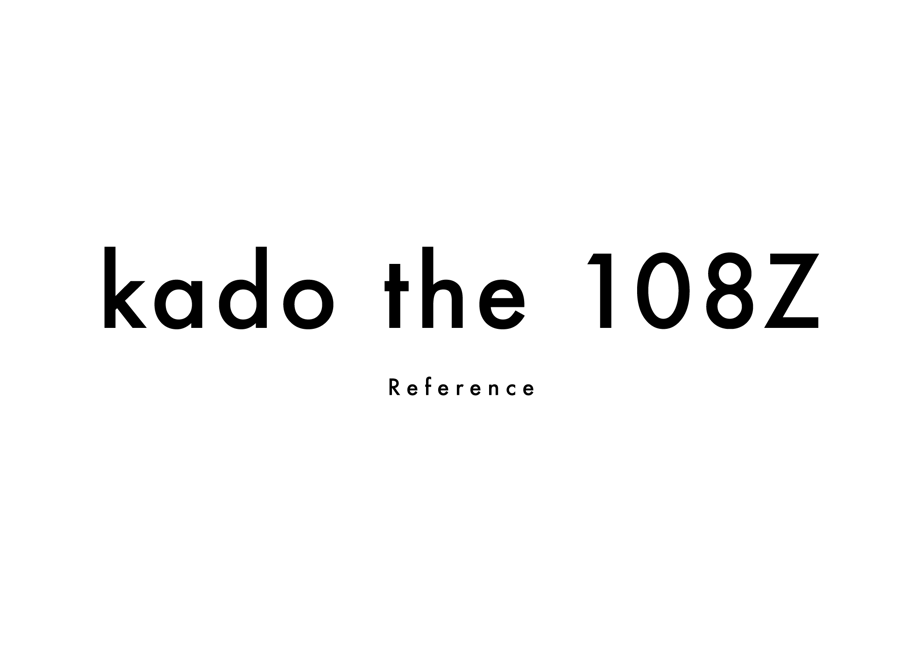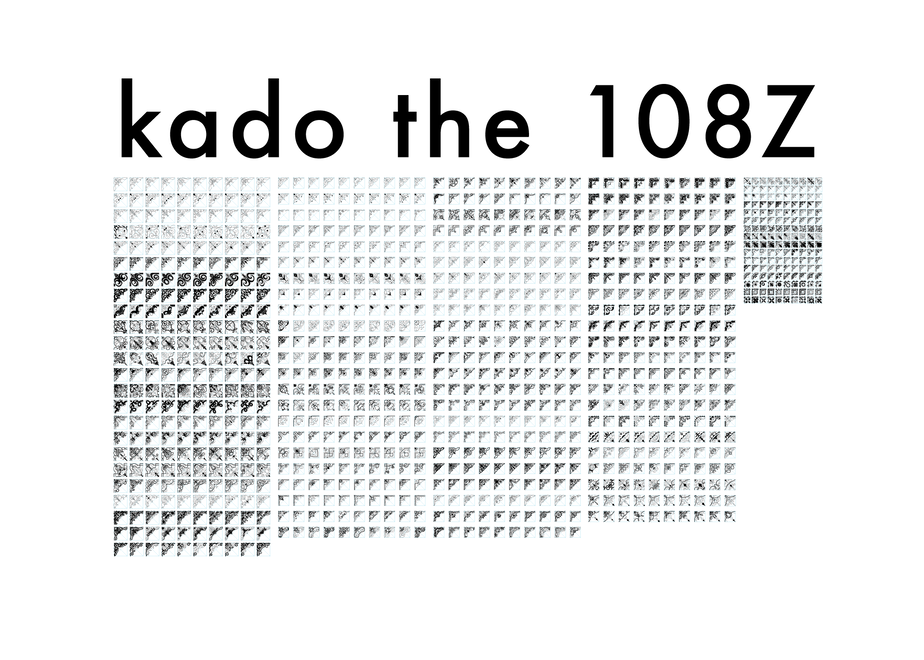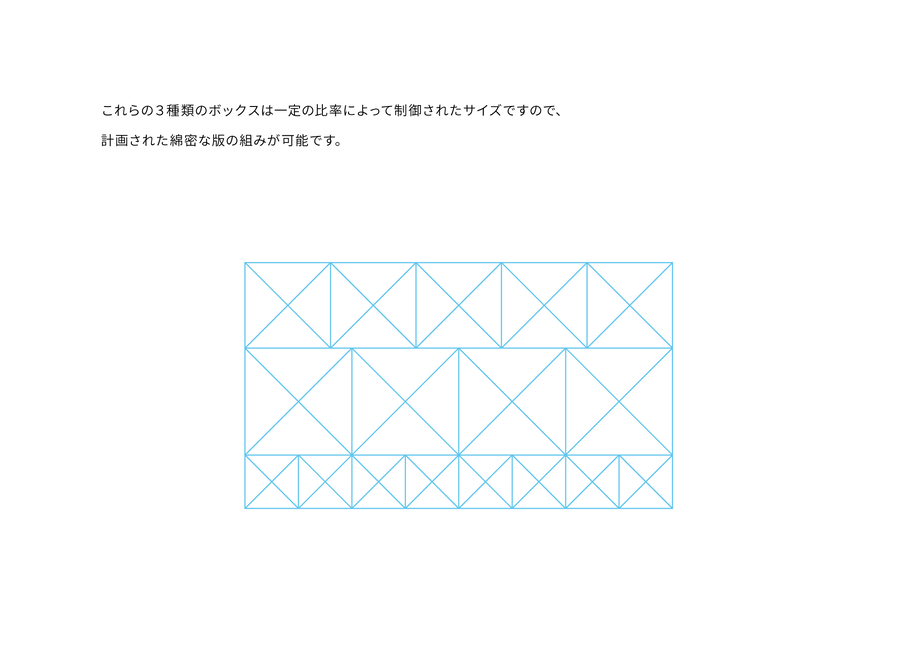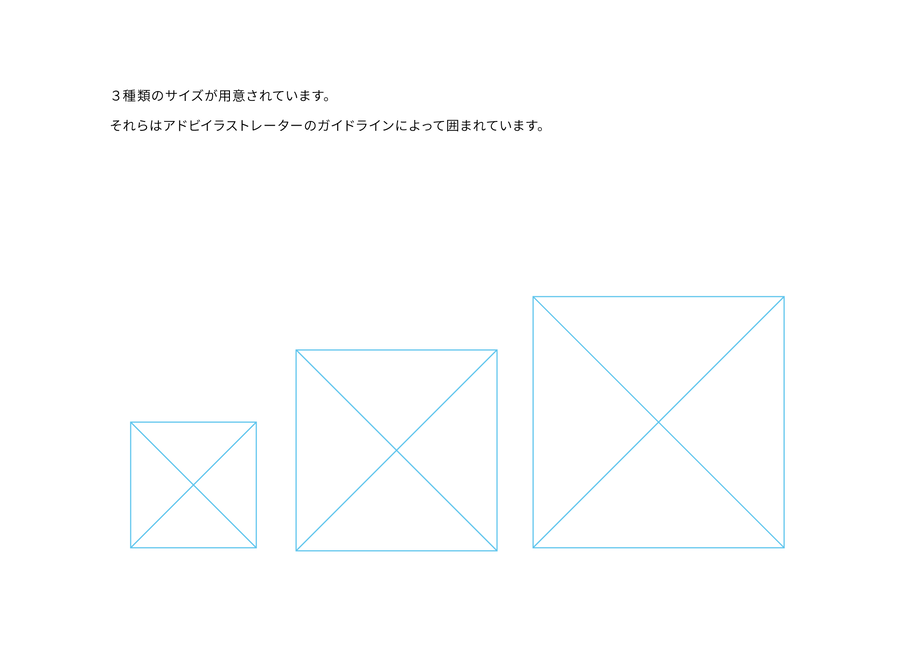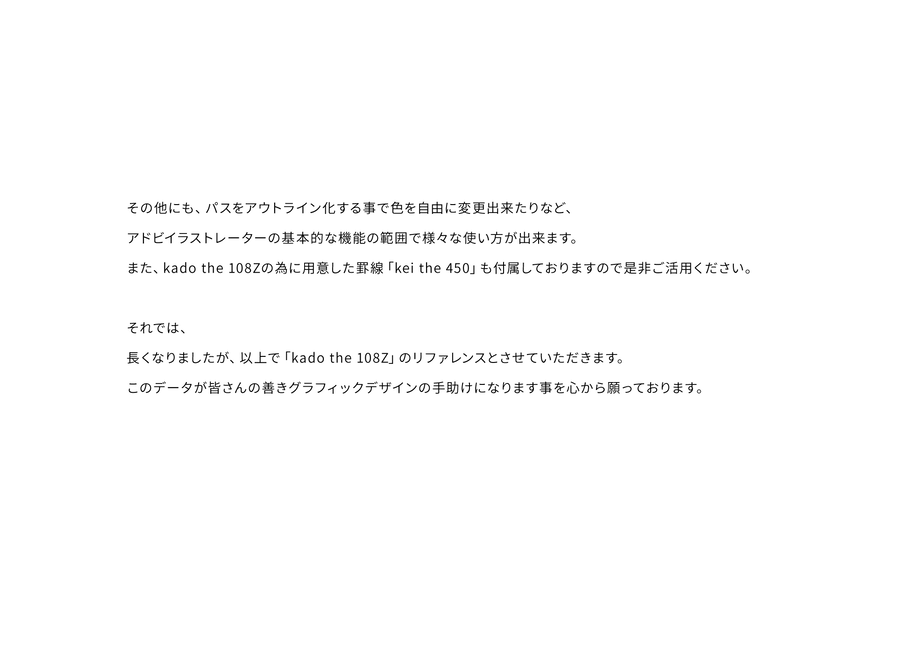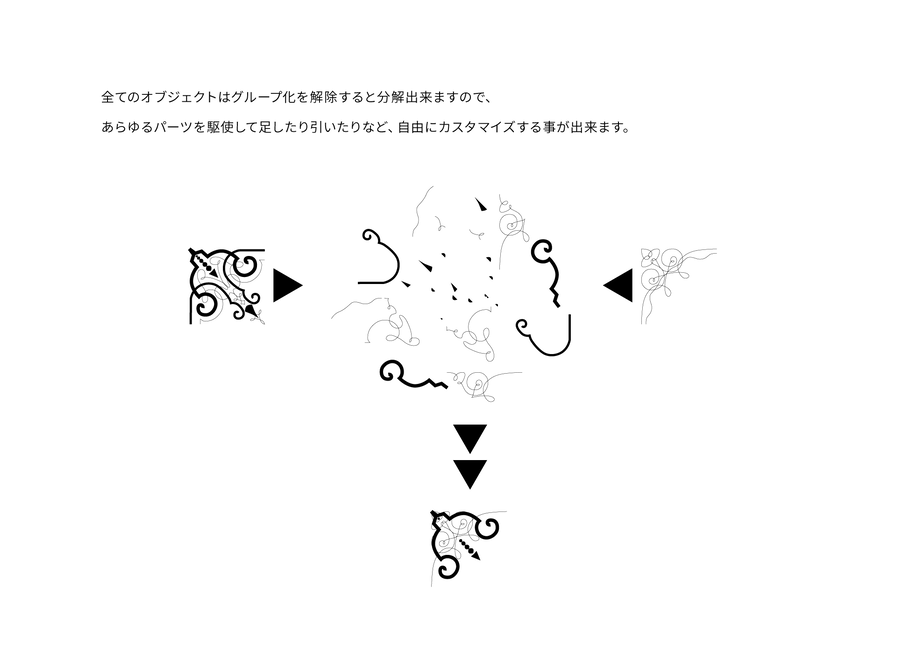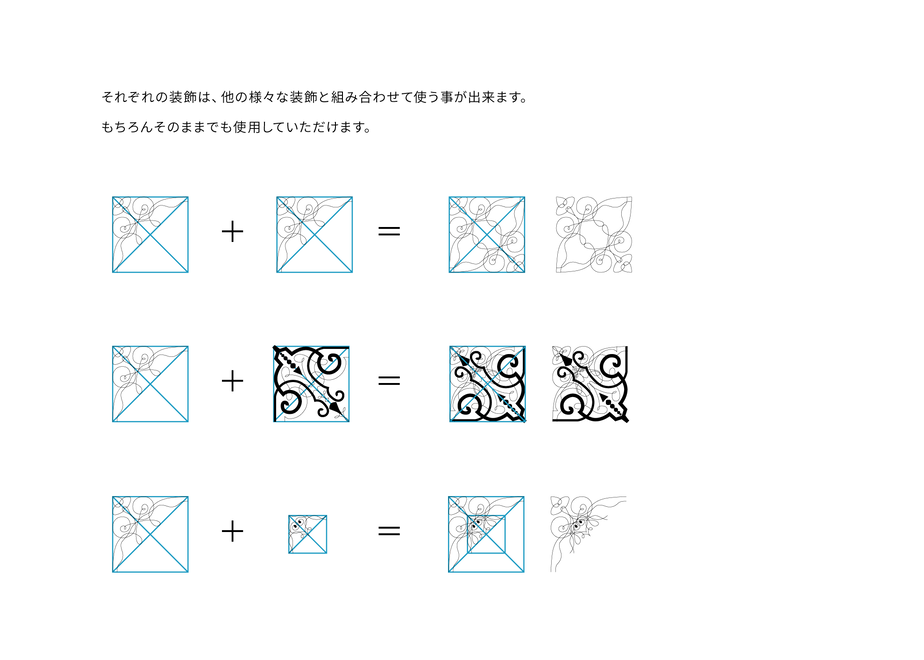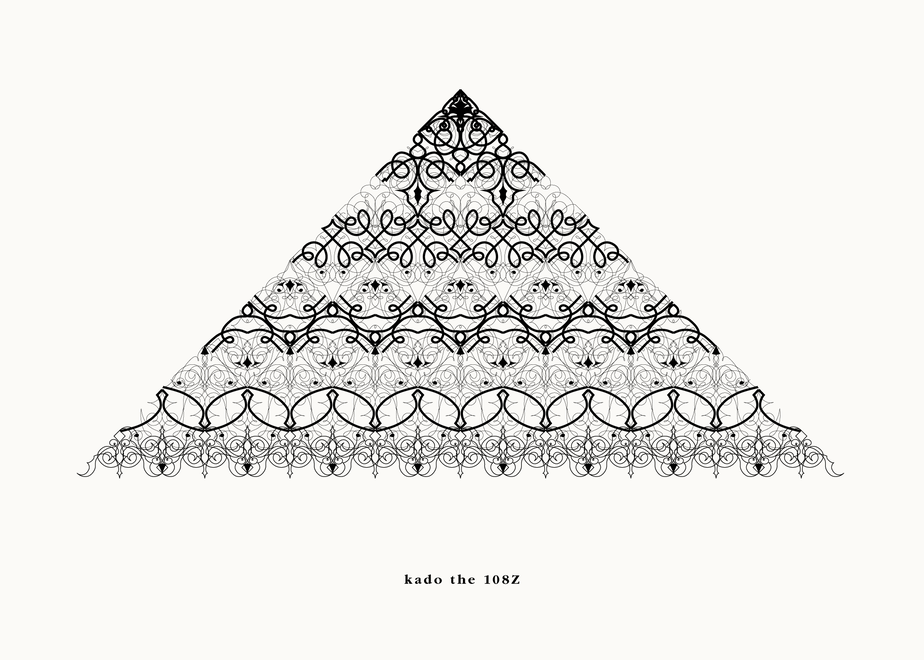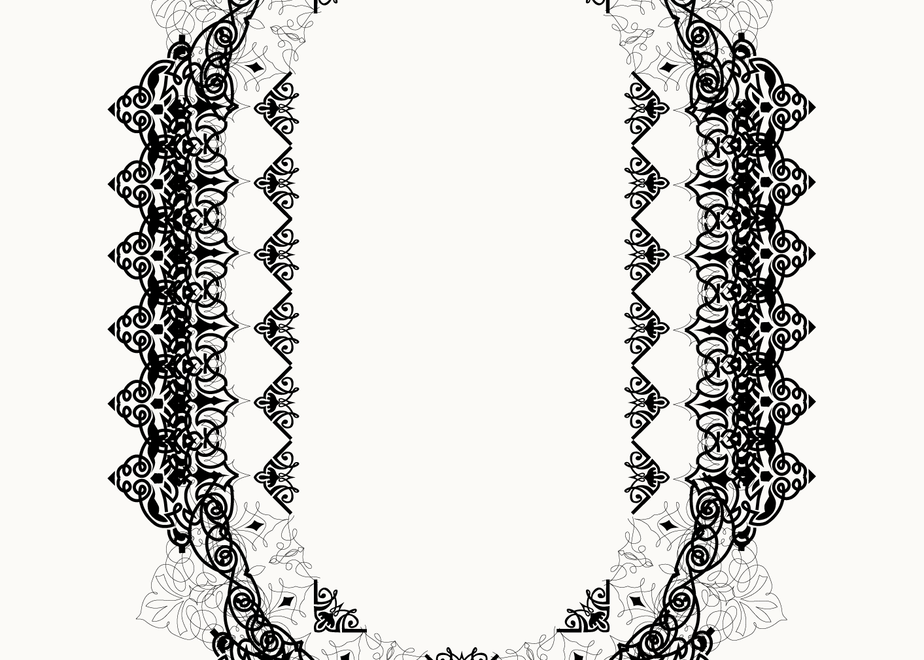
装飾活字:kado the 108Z
歴史的な印刷資料や装飾資料に収録された角飾りをもとに再構築した装飾活字コレクションです。
過去の文献から収集した108種類の角飾りをベースに、それぞれ10種類のバリエーションを制作。合計1,080種類の装飾オブジェクトとして再編集しています。
単なる資料の復刻ではなく、現代のデザイン環境でより柔軟に活用できるよう再設計を行い、Adobe Illustratorや各種デザインソフトウェアで利用しやすい形式にまとめています。
組み合わせによって無数の構成を生み出すことができるため、グラフィックデザイン、エディトリアルデザイン、ロゴ制作、パッケージデザインなど幅広い用途でご利用いただけます。
本商品は、歴史的な角飾りの意匠を現代の制作環境に合わせて再編集したオリジナルアーカイブコレクションです。
108系統の角飾りから派生した1,080種類のオブジェクトを収録しており、単体での使用はもちろん、組み合わせることで複雑な装飾やフレーム、レイアウトを構築することができます。
収録された組見本は、実際の活用例として自由に参照・応用していただけます。